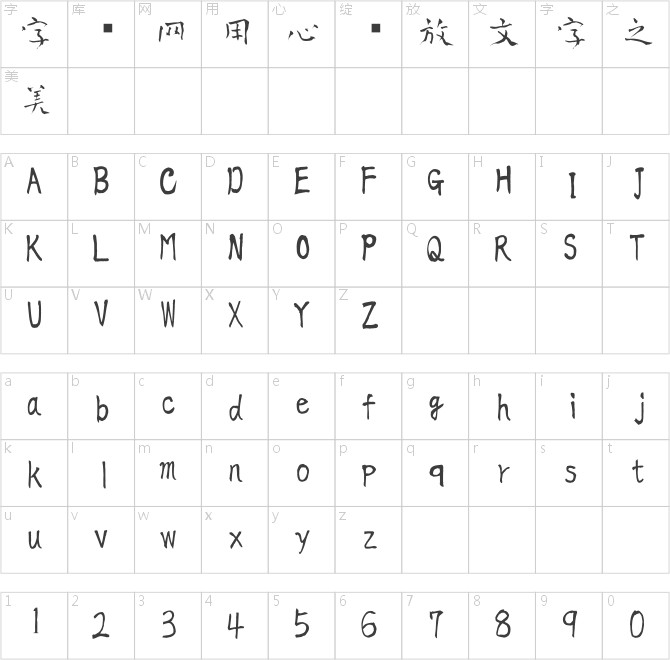
青柳疎石フォント字體下載AoyagiSosekiFont2
青柳疏石體是日本書法家青柳疏石老師揮毫創(chuàng)作的書法字體,青柳衡山先生負責將其它制作成字體文件。青柳疏石體這款字體看上去歪歪扭扭的極具特色,包含JIS第1水準2965字,第2水準3390字。由于字體采用的日本的JIS標準,所以支持的簡體字數(shù)不算多,但是繁體卻是比較齊全的。
青柳疎石フォント字體AoyagiSosekiFont2字庫是一款讓人賞心悅目、百看不厭的日文字體,適合各類廣告和產(chǎn)品包裝設(shè)計應(yīng)用,字體大小5.22MB,格式為ttf字體,上傳用戶是秦立華,作者/版權(quán)方為青柳疏石